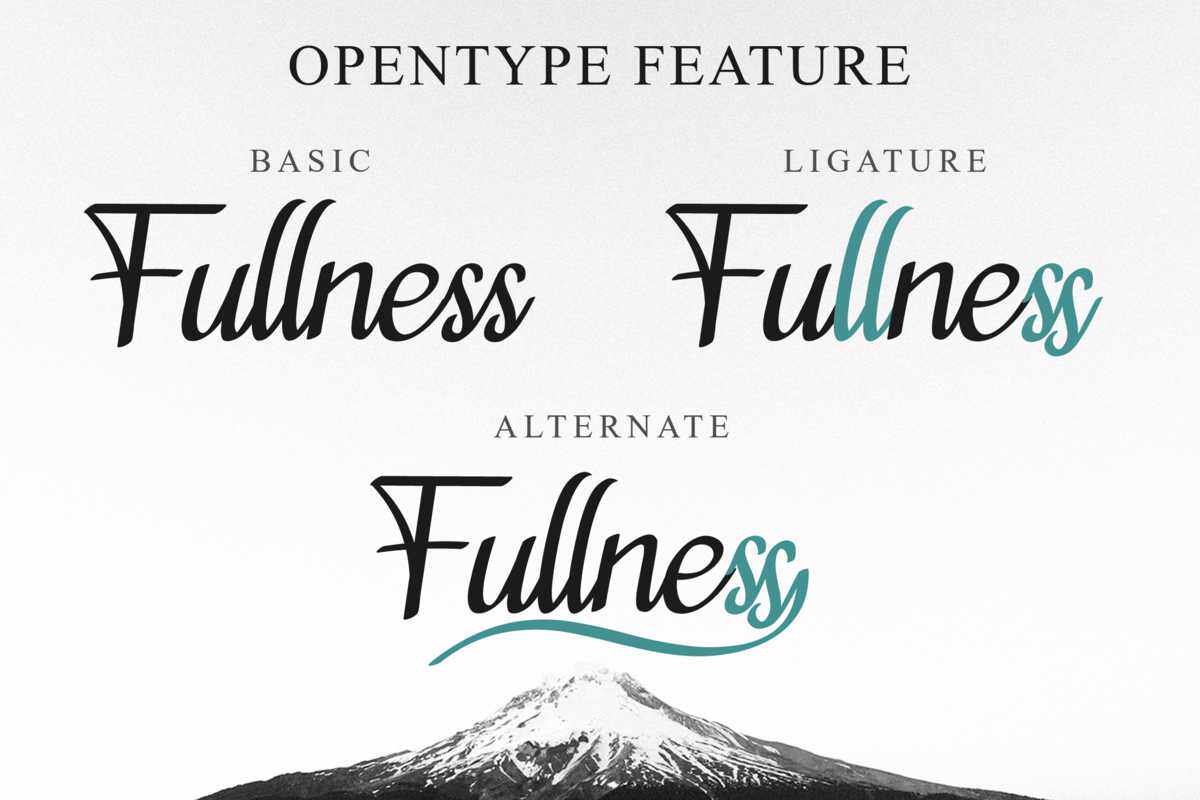
Viollevai是一款优雅而现代的智能字体,具有干净的外观,非常适合于商标、t恤设计、海报、名片、排版、报纸、其他设计项目和许多热媒运动。Viollevai将把任何创意都变成一件艺术品!Viollevai是一款优雅而现代的智能字体,具有干净的外观,非常适合于商标、t恤设计、海报、名片、排版、报纸、其他设计项目和许多热媒运动。Viollevai将把任何创意都变成一件艺术品!